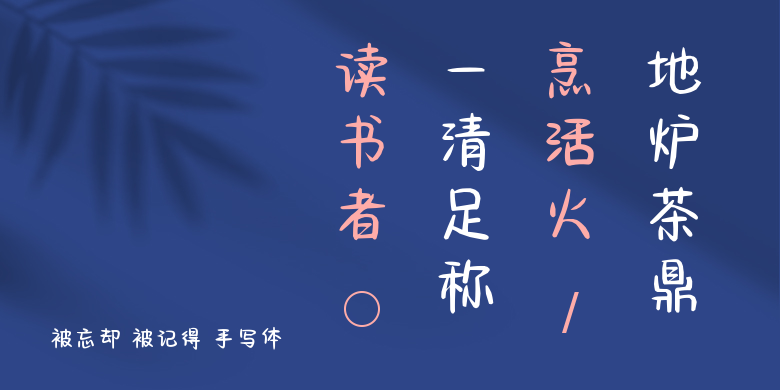
被忘却 被记得 手写体
被忘却 被记得 手写体,这款字体结构工整、笔画清晰,兼顾美观与易读性,适用于标题、正文、海报、包装、LOGO 等多种场景。字形优雅稳定,风格百搭耐看,适配日常排版与创意设计,让文字呈现更舒适、更具质感。被忘却 被记得 手写体一笔一画,皆是细节,以均衡的比例、流畅的线条打造舒适视觉体验,字形端正大气,风格简约现代。无论是商业设计、品牌宣传还是日常排版,都能轻松驾驭,让文字更有格调与力量。被忘却 被记得 手写体字体下载。